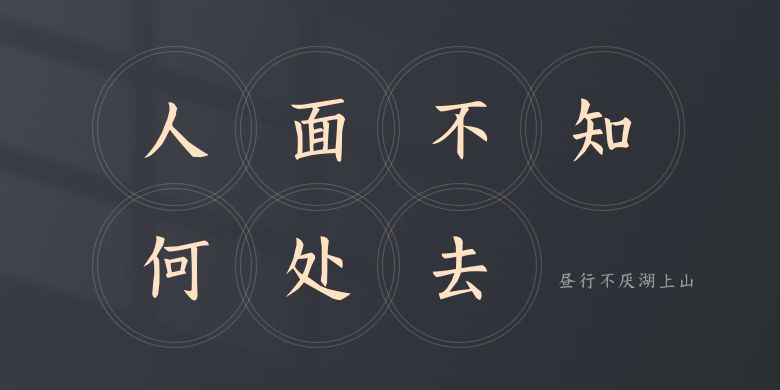
昼行不厌湖上山
昼行不厌湖上山,这款字体结构工整、笔画清晰,兼顾美观与易读性,适用于标题、正文、海报、包装、LOGO 等多种场景。字形优雅稳定,风格百搭耐看,适配日常排版与创意设计,让文字呈现更舒适、更具质感。昼行不厌湖上山一笔一画,皆是细节,以均衡的比例、流畅的线条打造舒适视觉体验,字形端正大气,风格简约现代。无论是商业设计、品牌宣传还是日常排版,都能轻松驾驭,让文字更有格调与力量。昼行不厌湖上山字体下载。